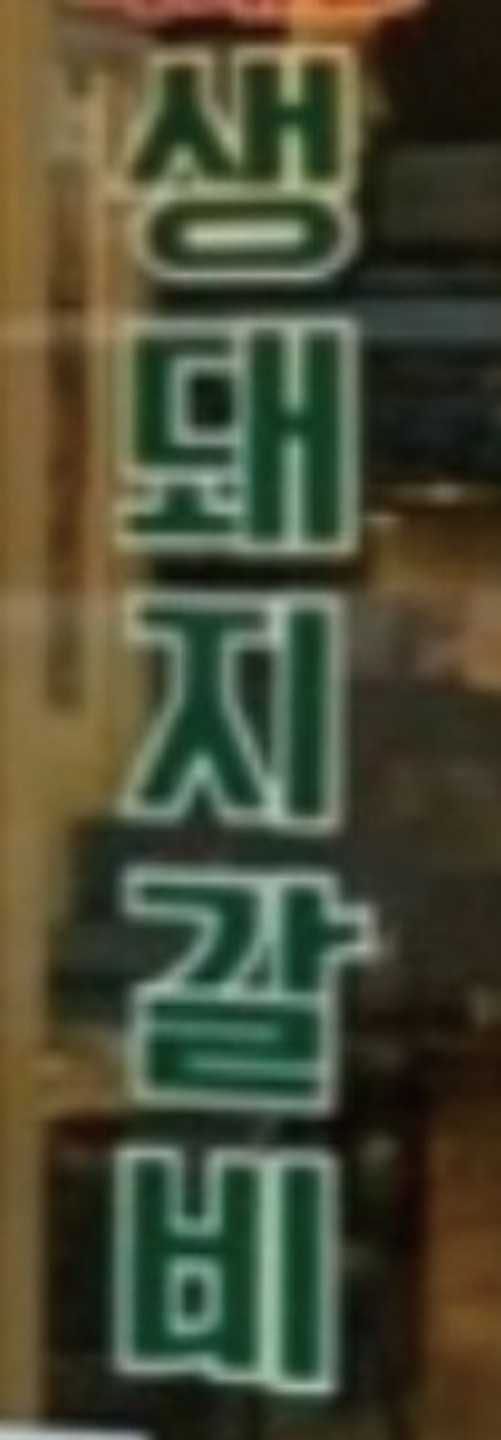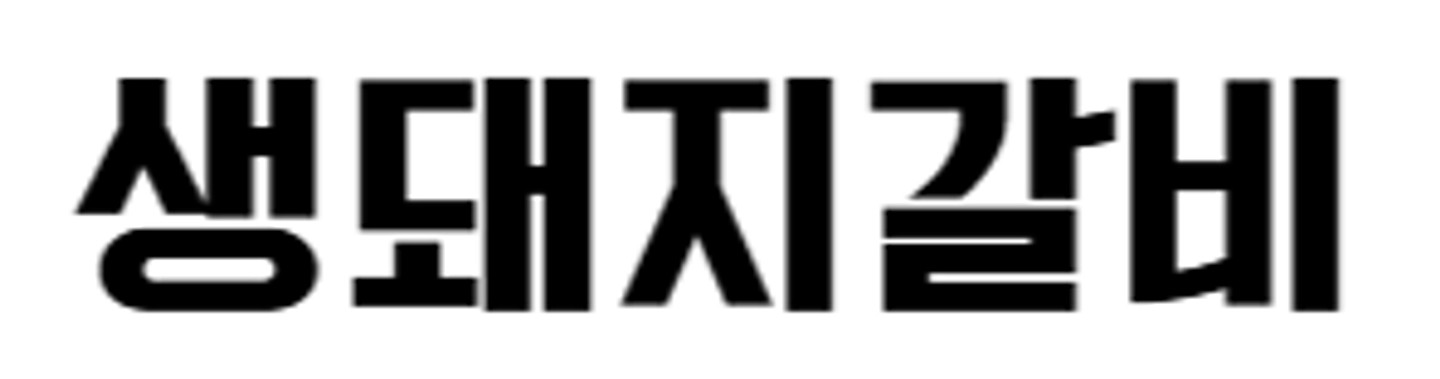
아시아폰트 옛날목욕탕
기본 폰트에서 가로사이즈를 늘려서 사용한 것 같습니다 https://www.asiafont.com/asfont/m_view.php?ps_db=sample&ps_boid=171&ps_page=1&ps_sele=subject&ps_ques=%EC%98%9B%EB%82%A0&ps_line=&ps_choi=&ps_divi=